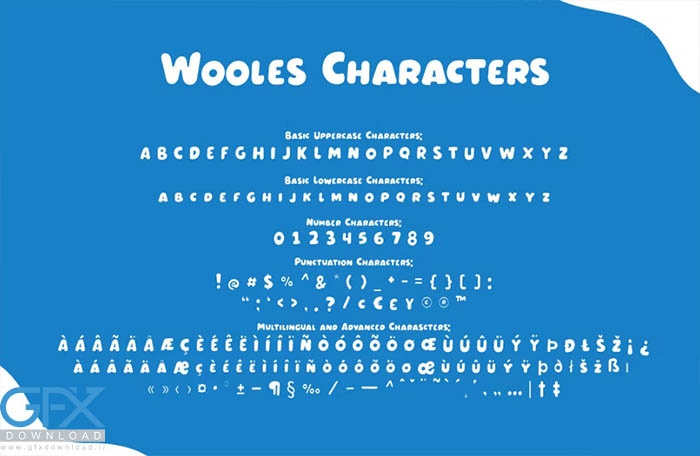
فونت رایگان کودکانه به سبک کمیک Wooles
فونت کودکانه به سبک کمیک Wooles
فونت رایگان کودکانه به سبک کمیک Wooles یک فونت با نمایش طنز و طراحی بازیگوش مناسب برای موضوعات کودکان است. این فونت رایگان زیبایی، و شادی را به ارمغان می آورد، با طراحی گرد، جسور و مدرن در یک بسته. کاملاً مناسب برای کودکان کتاب، طنز، مهد کودک، اسباب بازی، عنوان فیلم، بروشور، فناوری، پوستر، جلد کتاب، عنوان، عنوان، لوگو، مجله، بنر یا حتی آثار هنری در مقیاس بزرگ. WOOLES نسخه های معمولی و accents های چند زبانه دارد.